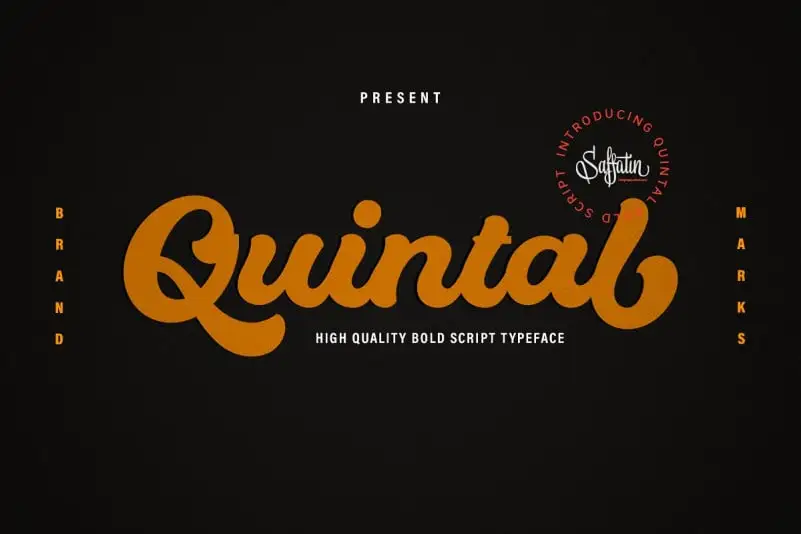
A Quintal Bold Script é uma elegante tipografia bold que se destaca na categoria dos scripts. Introduzida pela Saffatin Co., esta fonte traz um toque de diversão e criatividade à sua designação de texto, tornando-a especialmente atraente para conteúdo visual. Com um equilíbrio perfeito entre simplicidade e originalidade, o Quintal Bold Script é uma opção multifuncional que pode ser utilizada em diversos projetos. Seu carácter compacto permite que sejam facilmente integrados num conjunto de outros elementos gráficos, criando assim uma identidade visual única. À medida que você navega pelos caracteres desta fonte, experimentará a singularidade de cada letra como se estivessem vendo um filho gêmeo. Além disso, alguns ligaturas únicas e alternativas de letras tornam esta fonte ainda mais versátil, encorajando o seu potencial criativo. Esta é uma fonte perfeita para quem busca distinguir sua marca em um ambiente competitivo através da ilustração gráfica. Se você está procurando por algo novo e vibrante para enriquecer suas criações de design, a Quintal Bold Script pode ser exatamente o que está buscando.